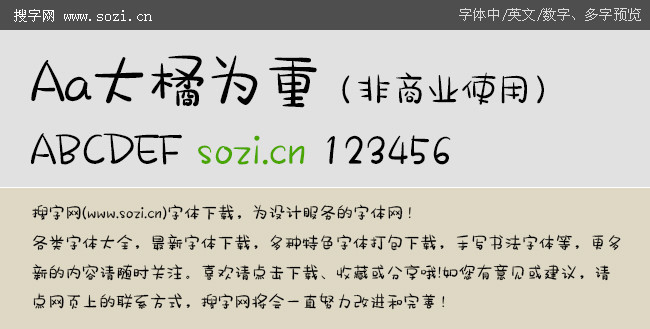
Aa大橘為重
搜字網(wǎng)給大家提供一款A(yù)a大橘為重(非商業(yè)使用)字體下載,該字體是一款不錯(cuò)的卡通藝術(shù)字體,這款字體風(fēng)格比一般的字體更有特色,連貫字跡顯得干練而不凌亂,清新簡(jiǎn)明,具有很好的視覺感。適合書裝設(shè)計(jì)、包裝設(shè)計(jì)、海報(bào)設(shè)計(jì)等應(yīng)用(此字體為個(gè)人非商用版,商用可以聯(lián)系QQ:1006760504)。